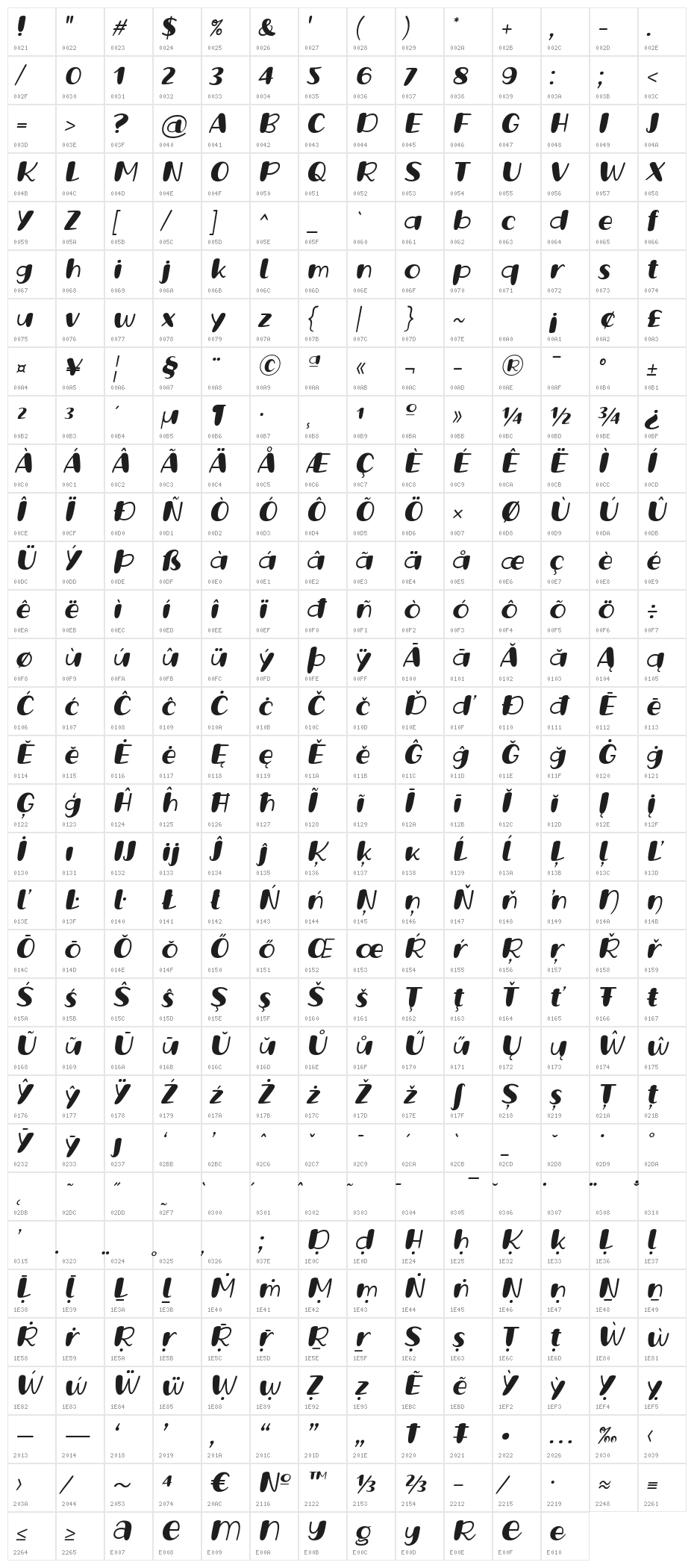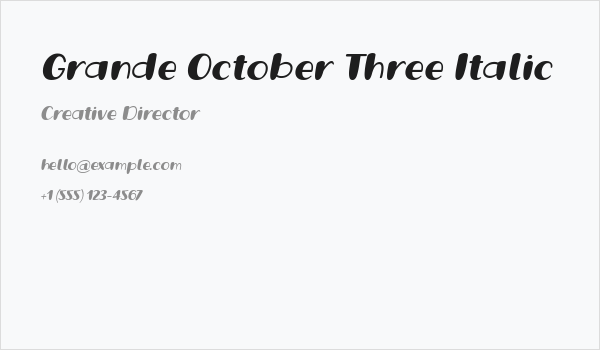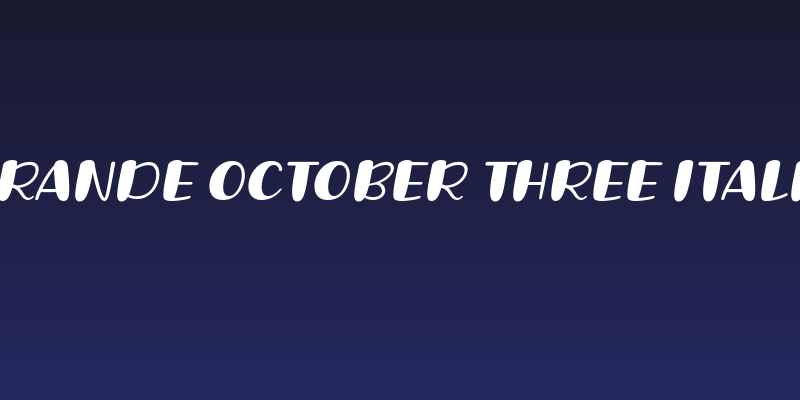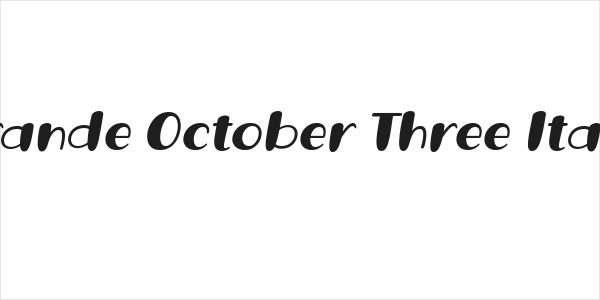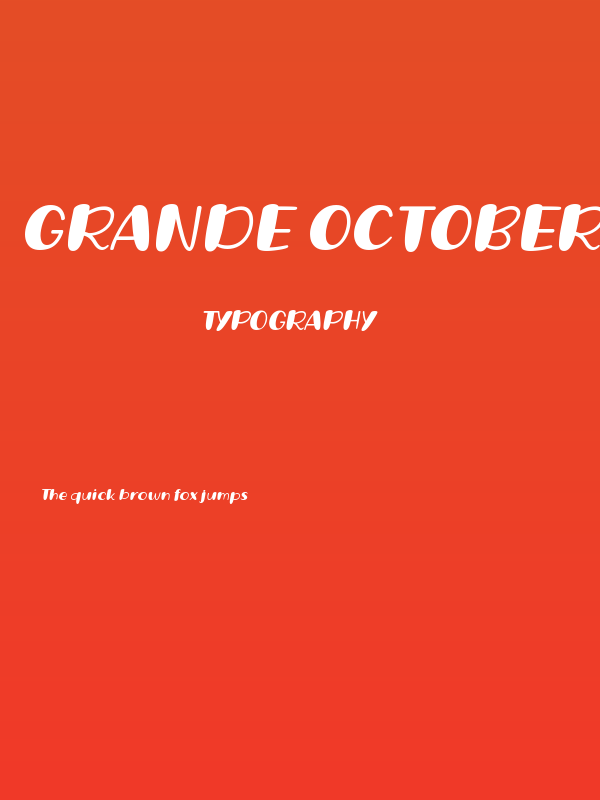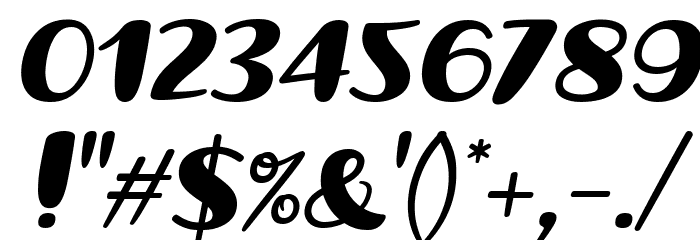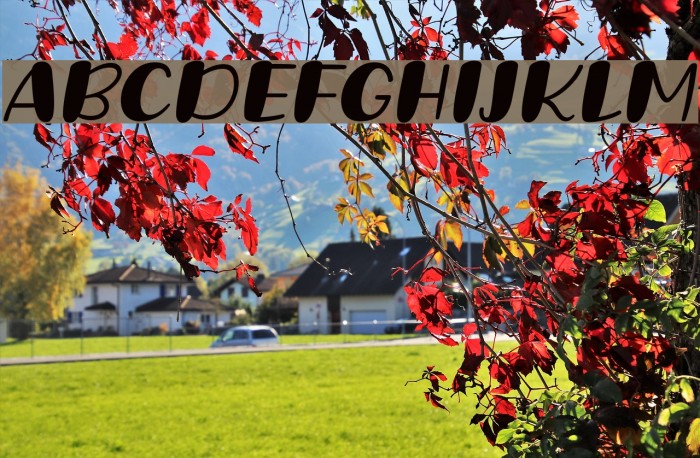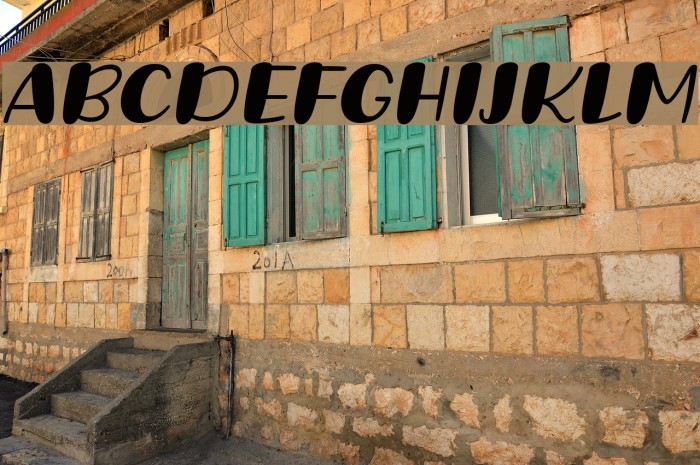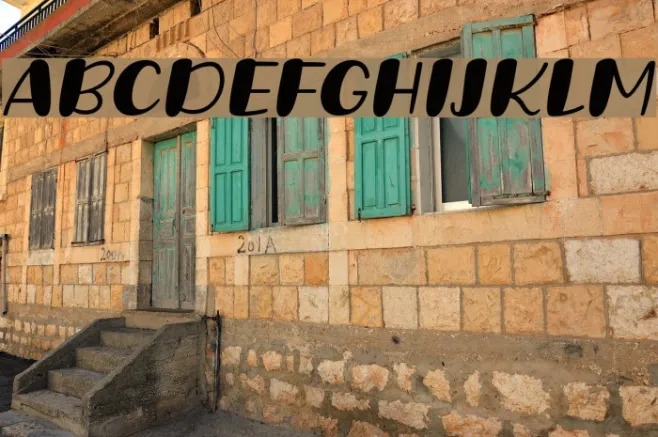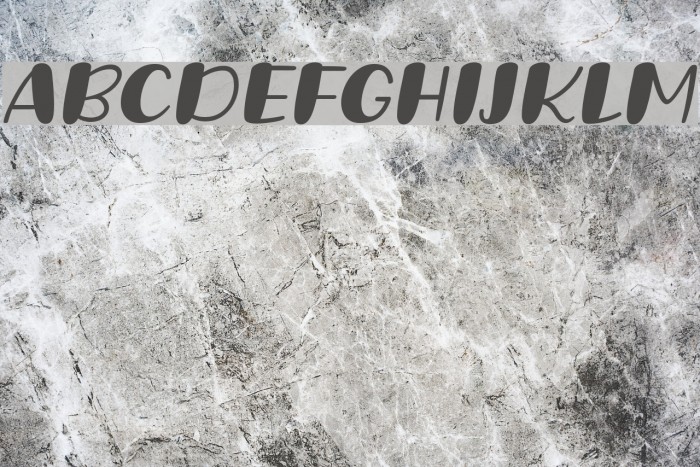
Grande October Three Italic Font
| Schriften Familie | Grande October Three |
| Anwendungsfall | Logos, Headlines, Invitations |
| Vorgeschlagene Projekte | Ideal for branding, invitations, greeting cards, and creative projects requiring a touch of elegance. |